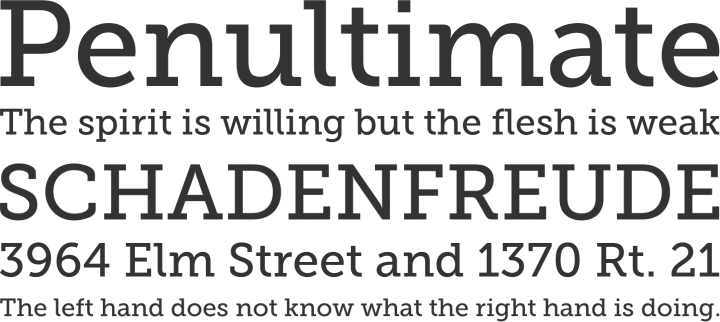
Новый шрифт Roboto Serif от Google делает чтение более удобным
Roboto Serif разработан таким образом, чтобы облегчить работу глаз и обеспечить идеальное качество чтения на экранах различных размеров и при печати.
Google и Commercial Type представили новый изменяемый шрифт под названием Roboto Serif. Шрифт с открытым исходным кодом удобен для глаз и обеспечивает идеальное качество чтения на экранах разных размеров и при печати.
Roboto Serif имеет минималистичный дизайн с «легким шепотом засечек». Шрифт был создан с нуля после множества экспериментов с различными формами и пропорциями, чтобы улучшить его читаемость. Roboto Serif имеет четыре переменные оси и шесть оптических размеров (микро, мелкий текст, текст, колода, дисплей и постер). Вы также можете настроить ширину, высоту, размер и уровень шрифта.
Google предоставляет девять готовых версий, включая Thin, ExtraLight, Regular, Medium, Bold и Black.
Roboto Serif — это семейство вариативных шрифтов, предназначенное для создания удобного и удобного чтения. Минималистичный и очень функциональный, он полезен где угодно (даже для интерфейсов приложений) благодаря обширному набору весов и ширин в широком диапазоне оптических размеров.
Roboto Serif — последнее дополнение к суперсемейству Roboto, в которое входят Roboto Sans, Roboto Slab, Roboto Mono и Roboto Condensed. Минималистичный дизайн и универсальность Roboto Serif отличают его от других шрифтов с переменными засечками, таких как Literata, которые предназначены в первую очередь для чтения с экрана. В поддерживаемых браузерах шрифт использует свойство CSS font-optical-sizing, чтобы улучшить качество чтения с экрана. Google говорит, что шрифт остается удобным для чтения в любом размере, в любом формате, от экрана до печати.
«Наша цель состояла в том, чтобы сделать шрифт, который вы могли бы использовать для длинных журналистских материалов или романа — что-то очень длинное и запутанное; захватывающий фрагмент текста, который вы читаете на своем телефоне — без желания жаловаться на это», сказал Грег Газдович из Коммерческого Типа.
Как мы и обещали в статье о 5 лучших шрифтах Google без засечек, сегодня мы поговорим о шрифтах с засечками в наших любимых шрифтах Google.
Чтобы представить это в контексте, мы должны начать с объяснения, что засечка — это маленькая линия, прикрепленная к концу штриха в букве или символе. Как мы видели, самым известным семейством шрифтов с засечками является «Times New Roman», который был с нами почти с нашего первого компьютера и до сих пор присутствует в прессе.
Используйте шрифты с засечками в своих издательских проектах
Мы сказали, что шрифты без засечек настоятельно рекомендуются для использования в веб-проектах , поскольку читабельность выше, когда они читаются с экрана; со шрифтами с засечками происходит обратное. Благодаря своим засечкам этот шрифт очень удобен для использования в длинных текстах, которые должны быть напечатаны . Ножки засечек помогают направлять взгляд по строкам текста, поэтому гораздо проще не потеряться и не перепутать строки.
Большинство газет используют шрифты с засечками в своих печатных изданиях, но не в онлайн-издании.
Есть несколько исключений, таких как abc.es (они чередуются с засечками и без засечек соответственно). Но, как мы уже говорили, удобочитаемость превыше всего.
Комбинации с засечками и без засечек
Что-то очень частое, что мы также делаем в SiloCreativo в цифровых проектах, — это комбинирование обоих шрифтов, вводя засечки в заголовки и без засечек в текст абзаца. Примеры таких сочетаний вы можете увидеть на нашем сайте, а также в этой статье о сочетаниях шрифтов.
Комбинации внутри одного семейства
Однако в этом случае, как и в случае со шрифтами без засечек, мы будем использовать только шрифты с засечками, комбинируя их в заголовках и абзацах. В отличие от шрифтов без засечек, следует отметить некоторые вещи.
В большинстве случаев семьи менее обширны; хотя это не означает, что они могут идеально сочетаться друг с другом, как мы увидим ниже. Мы можем нарисовать редакционный проект с 2 или 3 типами в одном семействе . Имейте в виду, как мы неоднократно говорили, что важно не смешивать слишком много.
Также отметим, что, хотя это и не является решающим, его использование рекомендуется (вообще) в строчных буквах, потому что в зависимости от шрифта засечки могут создавать противоположный эффект, снижая читабельность. Это происходит только в некоторых случаях, потому что этот же эффект может помочь нам, например, создавать потрясающие логотипы или сообщения.
Также можно сказать, что это один из типичных шрифтов с засечками. Он напоминает нам «Times New Roman», но с гораздо более элегантным и нетрадиционным стилем . Его элегантность делает его идеальным в качестве текстового заголовка в веб-проектах и текста абзаца в печатных проектах.
DROID SERIF
С таким характером, как Арво, но с меньшим авторитетом, это универсальный шрифт, идеально подходящий для использования в различных областях.